今回は書籍『幻綺行 完全版/横田順彌(著)、日下三蔵(編)』の使用フォントを紹介。本記事はデザイン構成において重要な「フォント」の選定プロセスや加工方法を、貴重なプロの実例から紐解いてデザイン制作に役立てる連載です。
レトロで武骨な印象の文字を使い古本のような趣を
困っている人を見捨てておけない性格ゆえ頻繁に事件に巻き込まれる快男児、中村春吉が、世界各地の秘境を探検して怪異や謎と対決するSF冒険譚『幻綺行 完全版/横田順彌(著)、日下三蔵(編)』。明治文化史や古本収集などの分野でも多くの業績を残したSF作家、横田順彌の魅力の詰まった作品で、単行本には未収録だった二篇を加えた完全版として新しく刊行された。ちなみに、中村春吉は明治期に実在した冒険家で、自転車での世界一周無銭旅行などで知られる。
表紙カバーは、昭和20~30年代に刊行されたポプラ社の「探偵冒険小説名作選」の装幀をリスペクトしたデザインに。レトロな雰囲気の装画や活字時代の名残を持つ書体、新たに作り起こされたオーナメント、シミや破れなどのダメージ加工で同レーベルの装幀を再現し、新刊でありながら圧倒的な古本感を漂わせる絶妙な趣となっている。
Font.01「AR明朝体U」
武骨さの残る極太の明朝体を選択
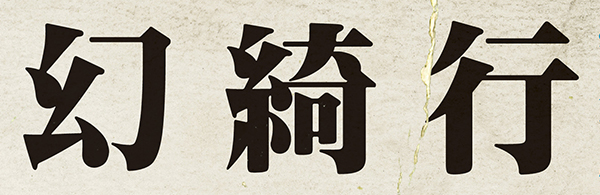
メインタイトルの文字は、見出しなどに用いられることを想定して作られた極太書体「AR明朝体U」(アーフィック)に。活字時代の名残のあるレトロな雰囲気の文字で、どこか武骨さの残るフォルムが表紙カバーのデザインコンセプトにマッチしていたため選択された。古本風の雰囲気に馴染むよう、ほんの少し角を丸めるなどの調整が加えられている。
Font.02「AR明朝体U」
タイトルと同じ明朝体でレトロ感を
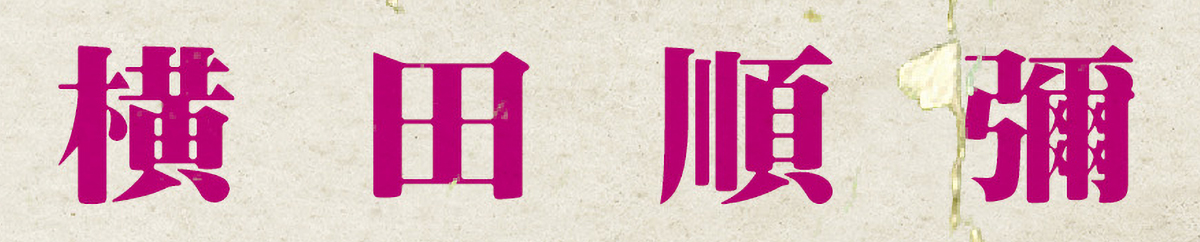
著者名部分は、タイトルと同じ極太の明朝体「AR明朝体U」(アーフィック)に。ポプラ社の「探偵冒険小説名作選」の装幀を意識し、若干平体をかけたり、角を丸めたり、線を痩せさせるなどの調整が施されている。
Font.03「AR明朝体U」
レトロ感を強調するため他のフォントもそろえる
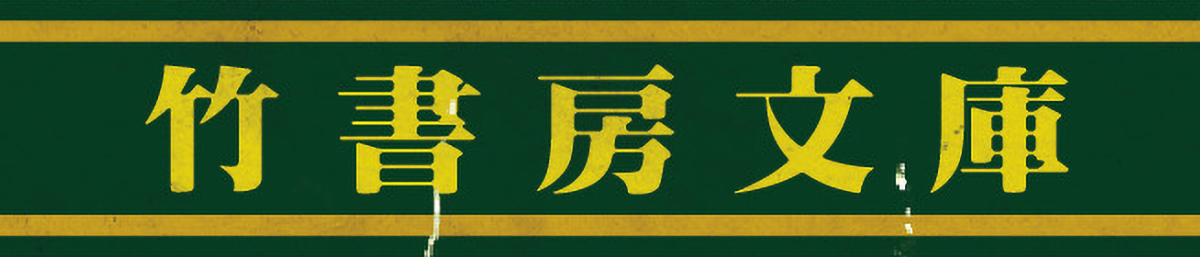
レーベル名「竹書房文庫」部分も他の文字要素と同じ「AR明朝体U」(アーフィック)に。レトロな雰囲気を強めるため、若干平体をかけたり、角を丸めたり、線を痩せさせるなどの調整がされている。